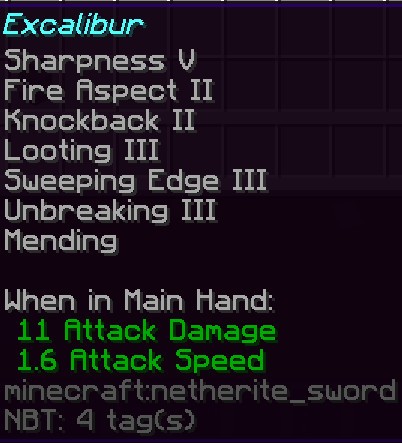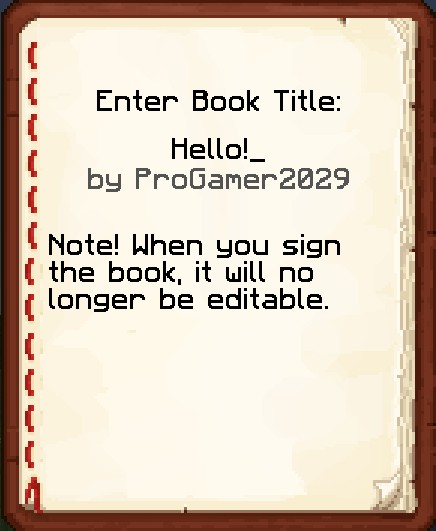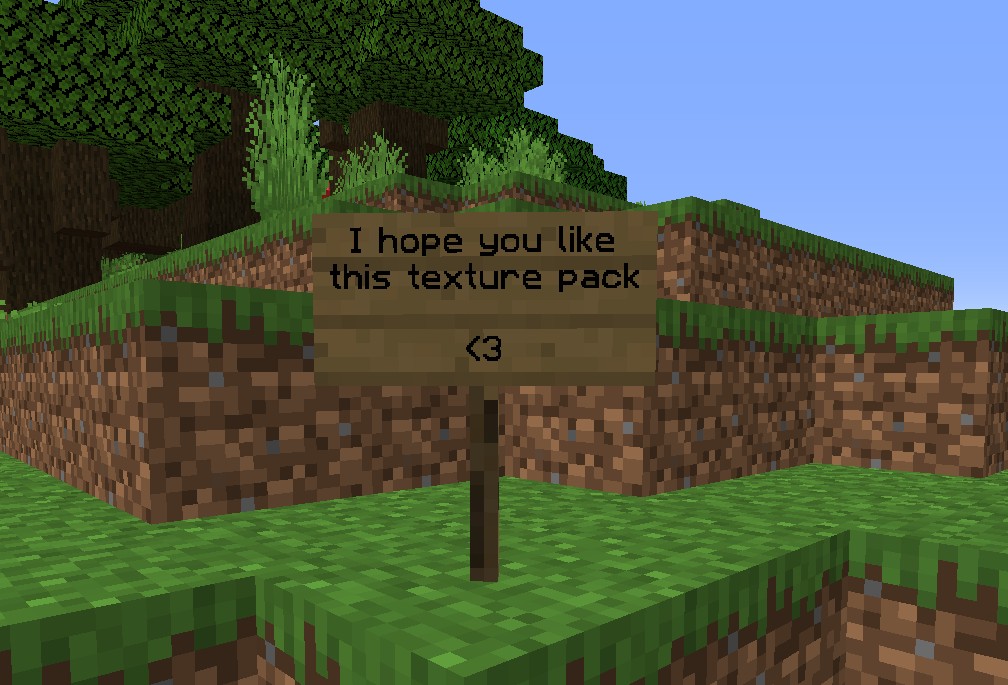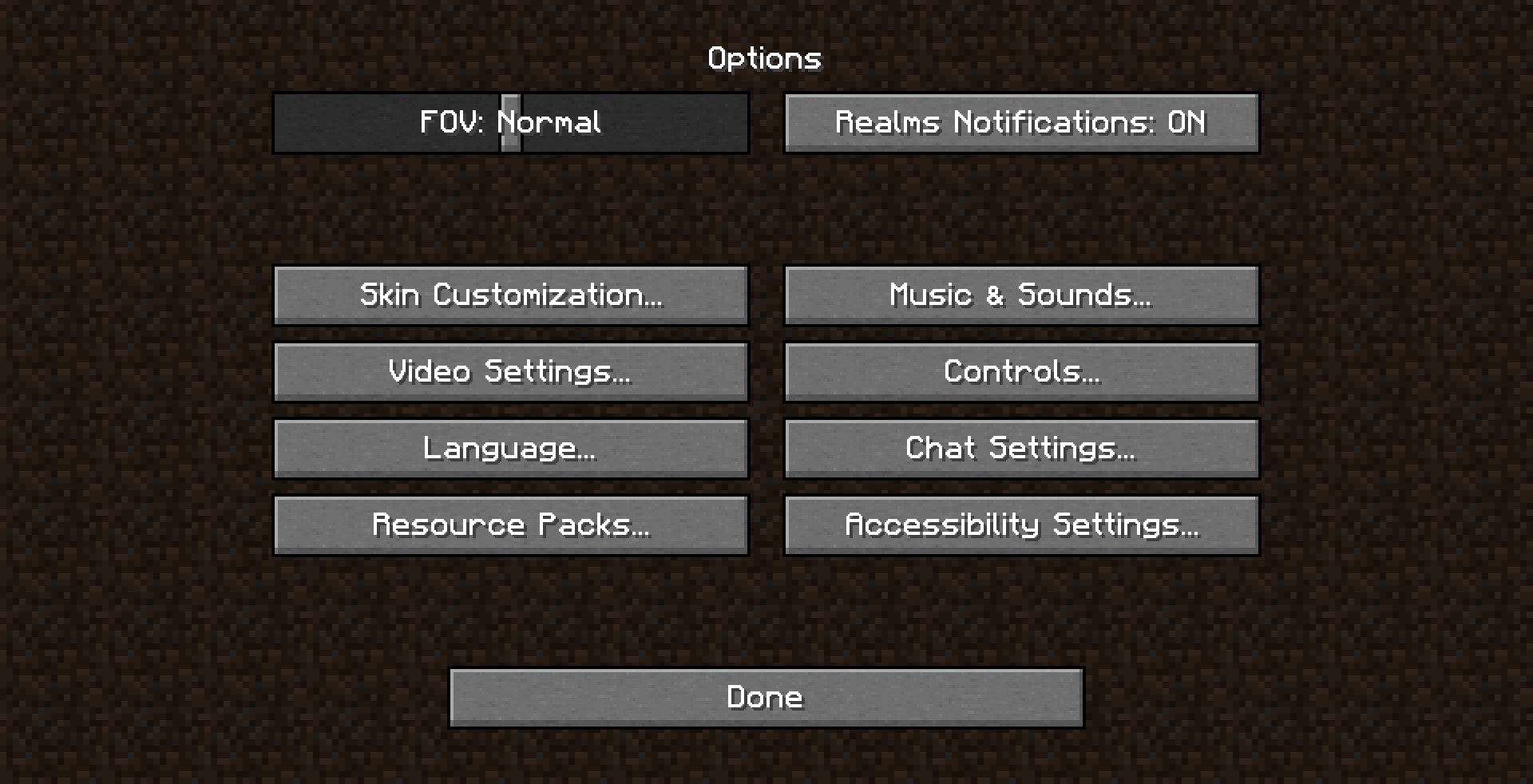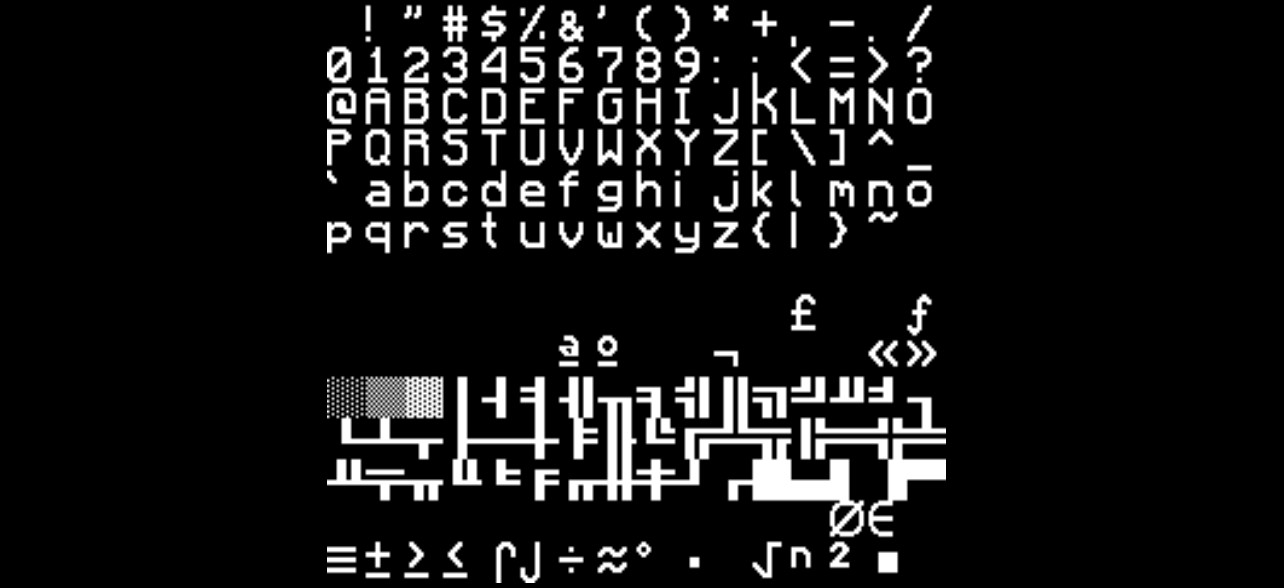
Улучшите восприятие текста в игре для большего комфорта.
Почувствуйте разницу в визуальном восприятии с модом Smooth Font - 32x для Minecraft версии 1.21! Если шрифт в игре кажется вам странным или нестандартным, этот мод станет идеальным решением. Разработанный на основе популярного текстурного пакета Faithful 32, он изменяет только текстовые элементы игры: буквы, цифры и другие символы, улучшая их четкость и читаемость.
Многие игроки сталкиваются с проблемами восприятия текста в Minecraft, и именно здесь на помощь приходит наш мод. Он не только улучшает визуальные характеристики, но и создает более приятное пользователям окружение, что делает игру более комфортной.